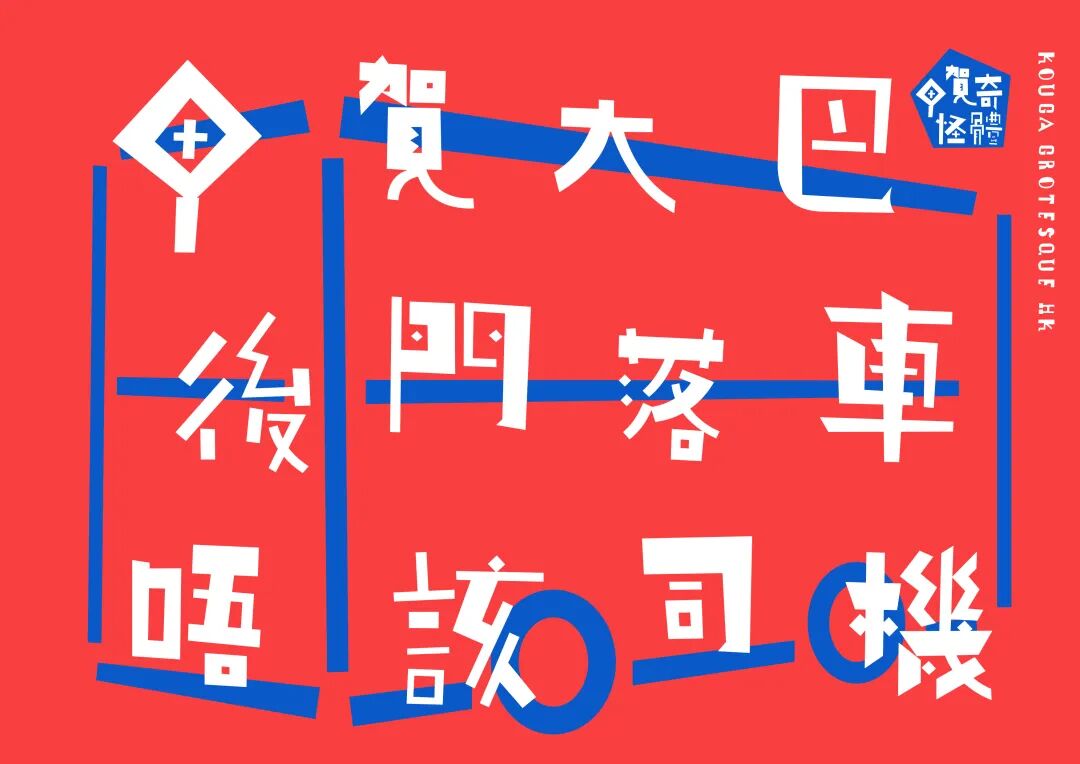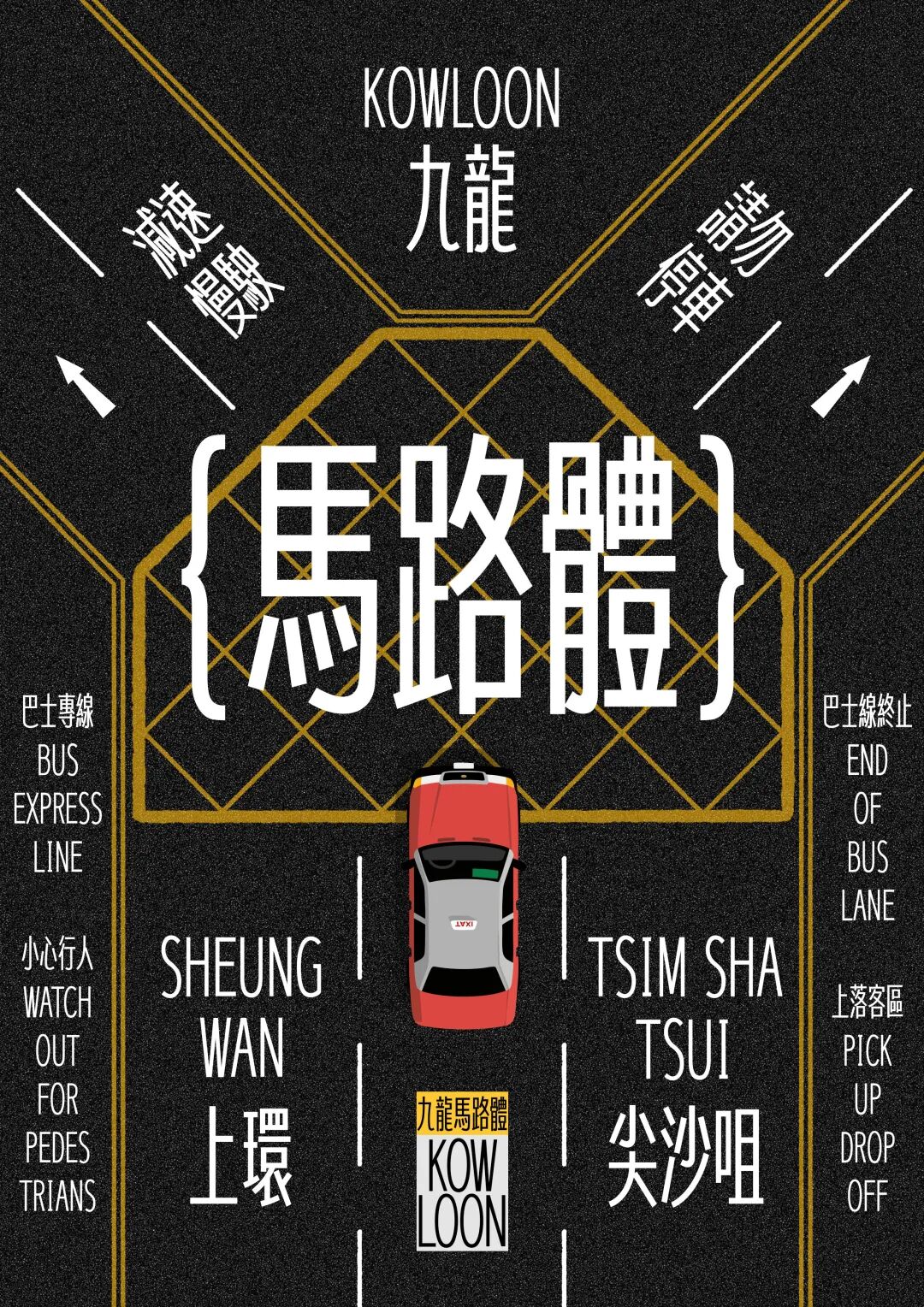
喜報 | NICETYPE HK字體作品勇奪第十六屆 Hiiibrand Awards 國際品牌及傳達設計大獎
2026 年 5 月 11 日,第十六屆 Hiiibrand Awards 國際品牌 & 傳達設計大獎 公佈得獎名單。
NICETYPE HK 旗下兩款原創字體——Kouga Grotesque HK(TypeinHK甲賀奇怪體) 與Nicetype Kowloon Road HK(香港字造九龍馬路體),喺全球 40 多個國家、1,733 件作品中雙雙入圍「漢字字體設計·專業組」,真係實力證明!
呢兩款字體真係靚到爆燈,喺國際舞台拎獎,真係為香港字造爭光!
TypeinHK甲賀奇怪體字型
香港字造九龍馬路體字型
香港字造,世界共賞
NICETYPE HK 秉承「香港字造」嘅精神理念,透過字體設計,連繫香港嘅過去、而家同未來,畀文字成為展現香港文化魅力嘅窗口。佢哋持續用字體去演繹香港獨特嘅語言特色同城市精神,呼應「香港製造」對品質同本土特色嘅堅持,亦為「香港品牌」注入咗文化厚度同獨特辨識度。
品牌團隊一直好用心咁深入探索香港嘅語言文化同視覺美學,細心挖掘歷史入面好多珍貴嘅符號,將香港獨有嘅地標意象、有趣嘅方言節奏,甚至係充滿質感嘅建築紋理,巧妙拆解再融入字體設計嘅細節之中。每一款字體嘅誕生,都係對香港文化基因嘅精准解讀,同時都係對城市精神嘅生動演繹。
NICETYPE HK 會繼續以「在地共生」為核心,用先鋒、無畏嘅態度,探索漢字嘅無限可能,讓香港字造嘅力量,繼續喺國際舞台發聲!